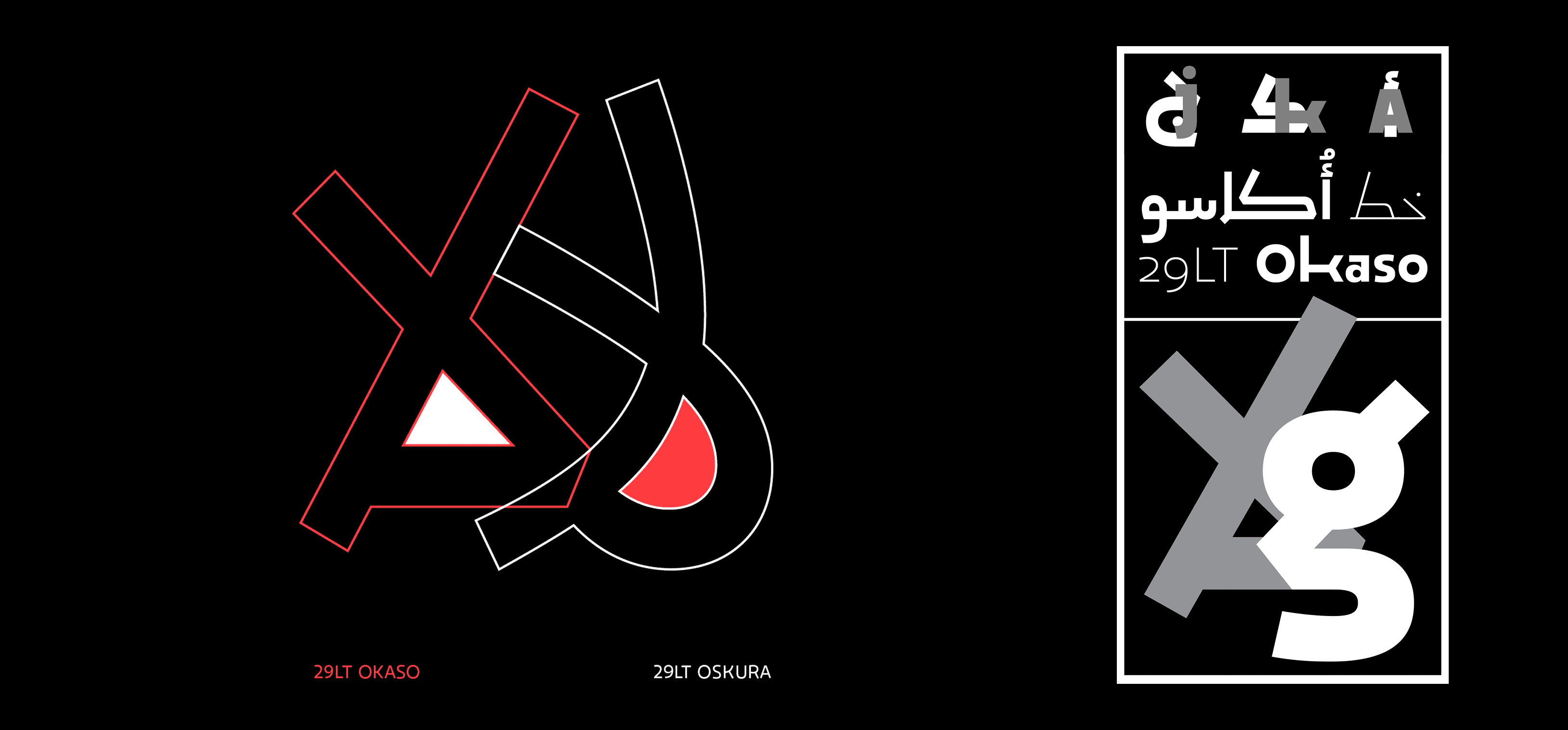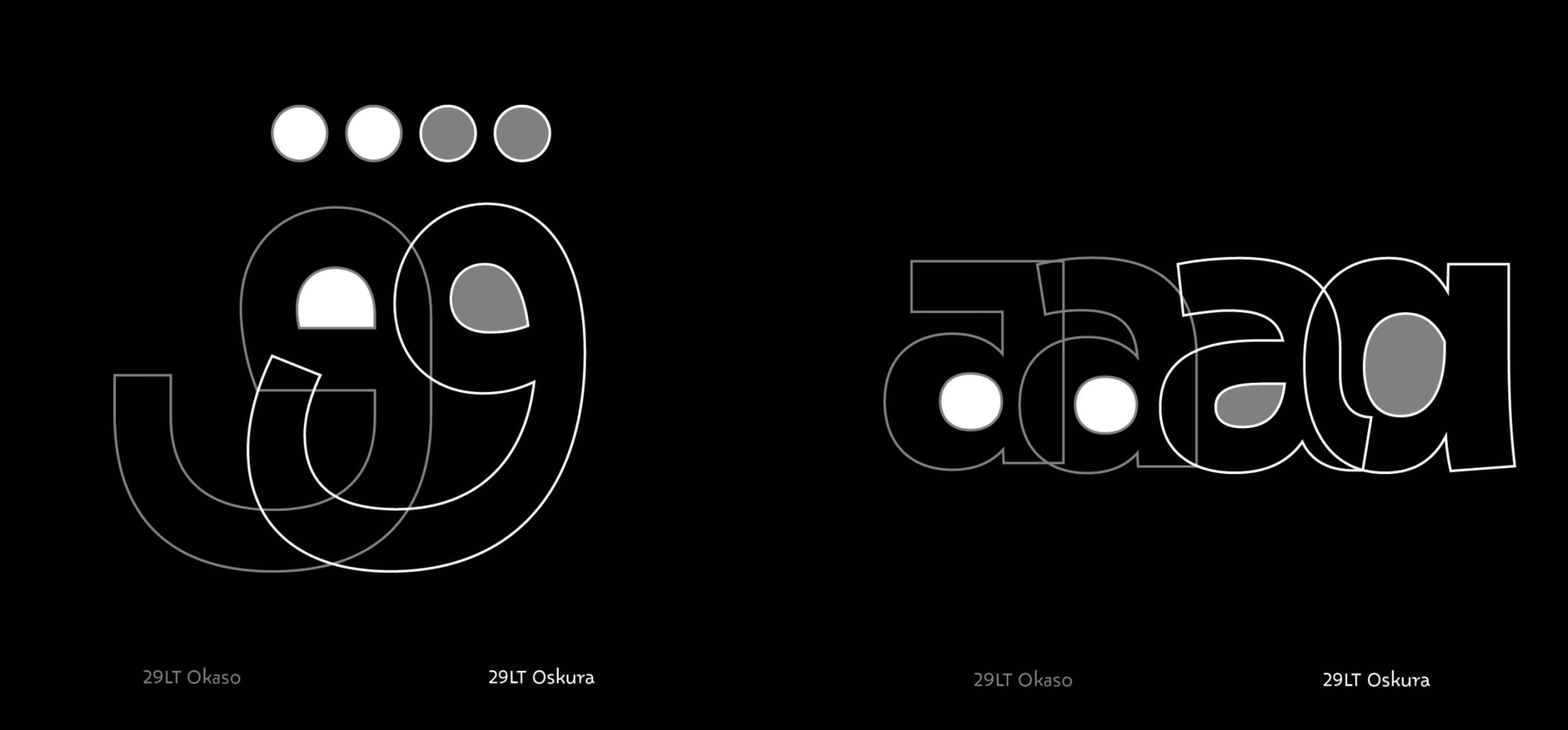
يتميّز 29LT Oskura بتصميم مستوحى من المخطوطات الإسلامية الكلاسيكية، مع لمسة هندسية معاصرة تعبّر عن التوازن بين الروحانية والدقة البصرية. يمتد الخط عبر مجموعة واسعة من الأوزان، مما يجعله مثاليًا للنصوص التحريرية، الشعر، والنشر الإبداعي.